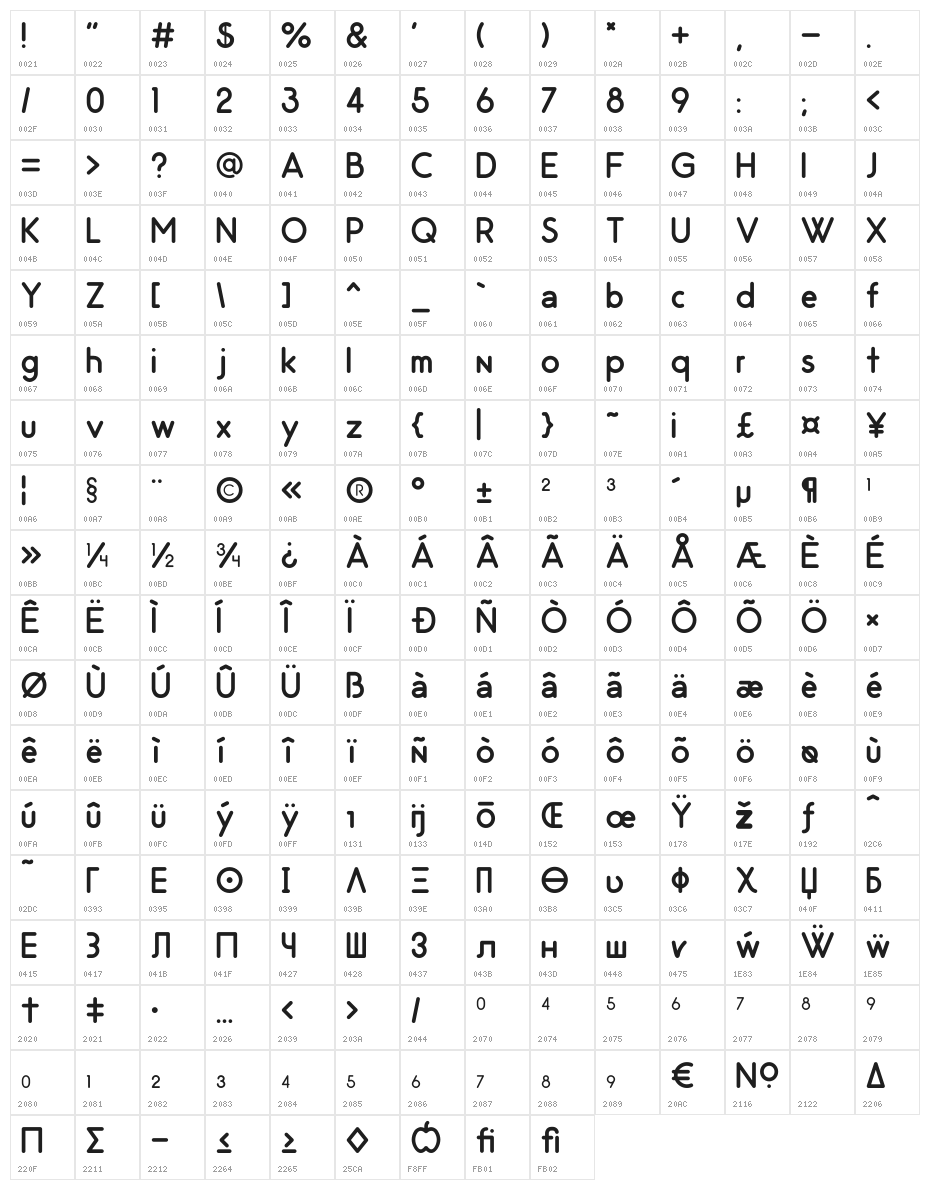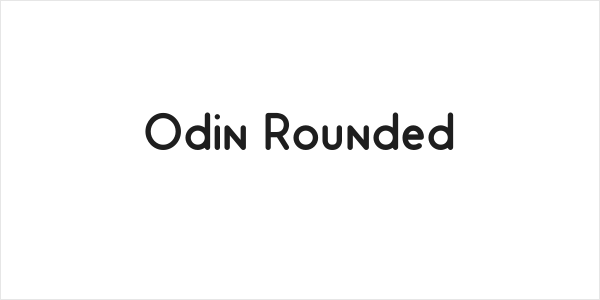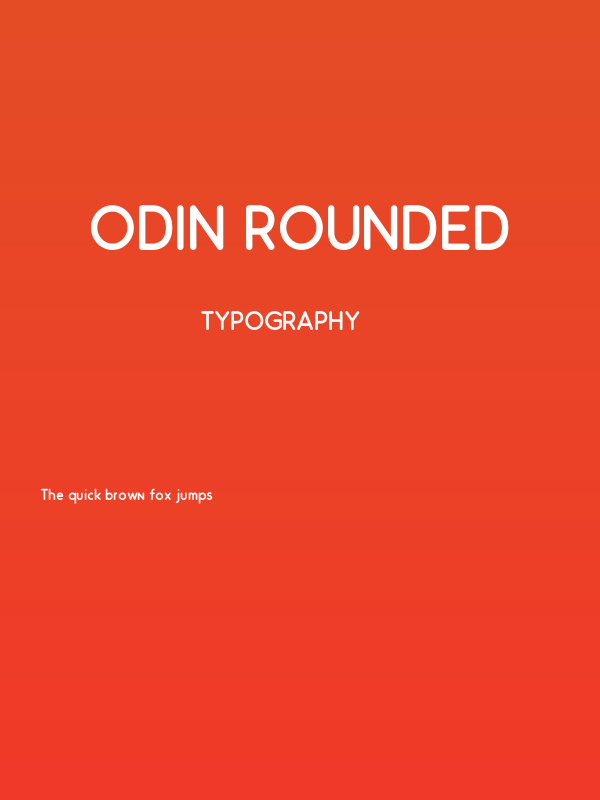
Odin Rounded Font
| 使用场景 | Headlines, Body text, Logos |
| 推荐项目 | Ideal for branding, advertising, web design, and user interfaces where a modern and friendly tone is desired. |